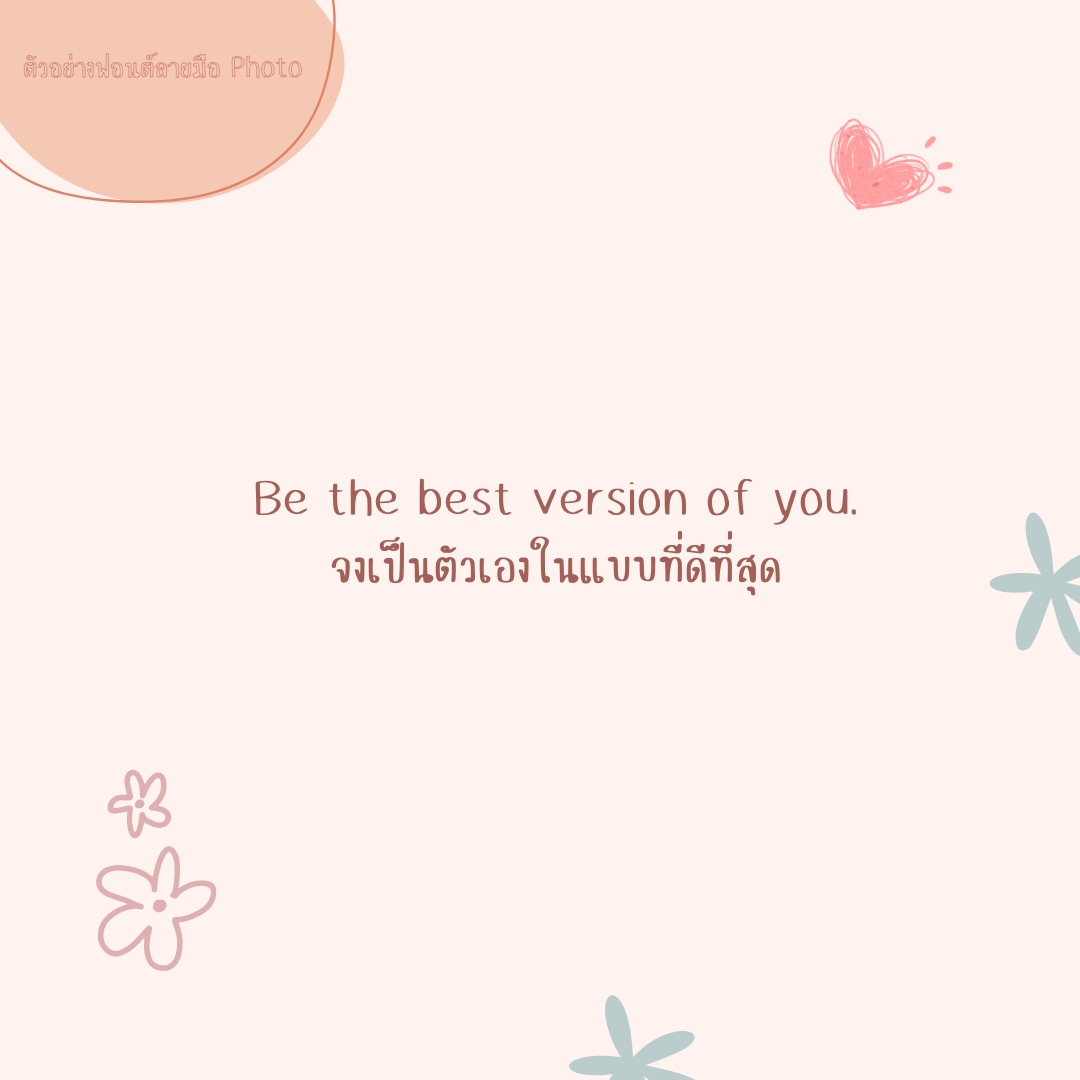
Photo
แจกฟรี!!!! ฟอนต์ลายมือ Photo
Photo เป็นฟอนต์ลายมือที่ผสมความมินิมอล+ลายมือแบบไทย ๆ นิดหน่อยได้แบบลงตัว เหมาะกับงานที่ต้องใช้ฟอนต์ทุกชนิด ไม่ว่าจะงานพิมพ์ ออกแบบ จดสรุปก็ย่อมเหมาะเพราะน้อนเป็นฟอนต์ที่เรียบ ๆ เบสิค ๆ